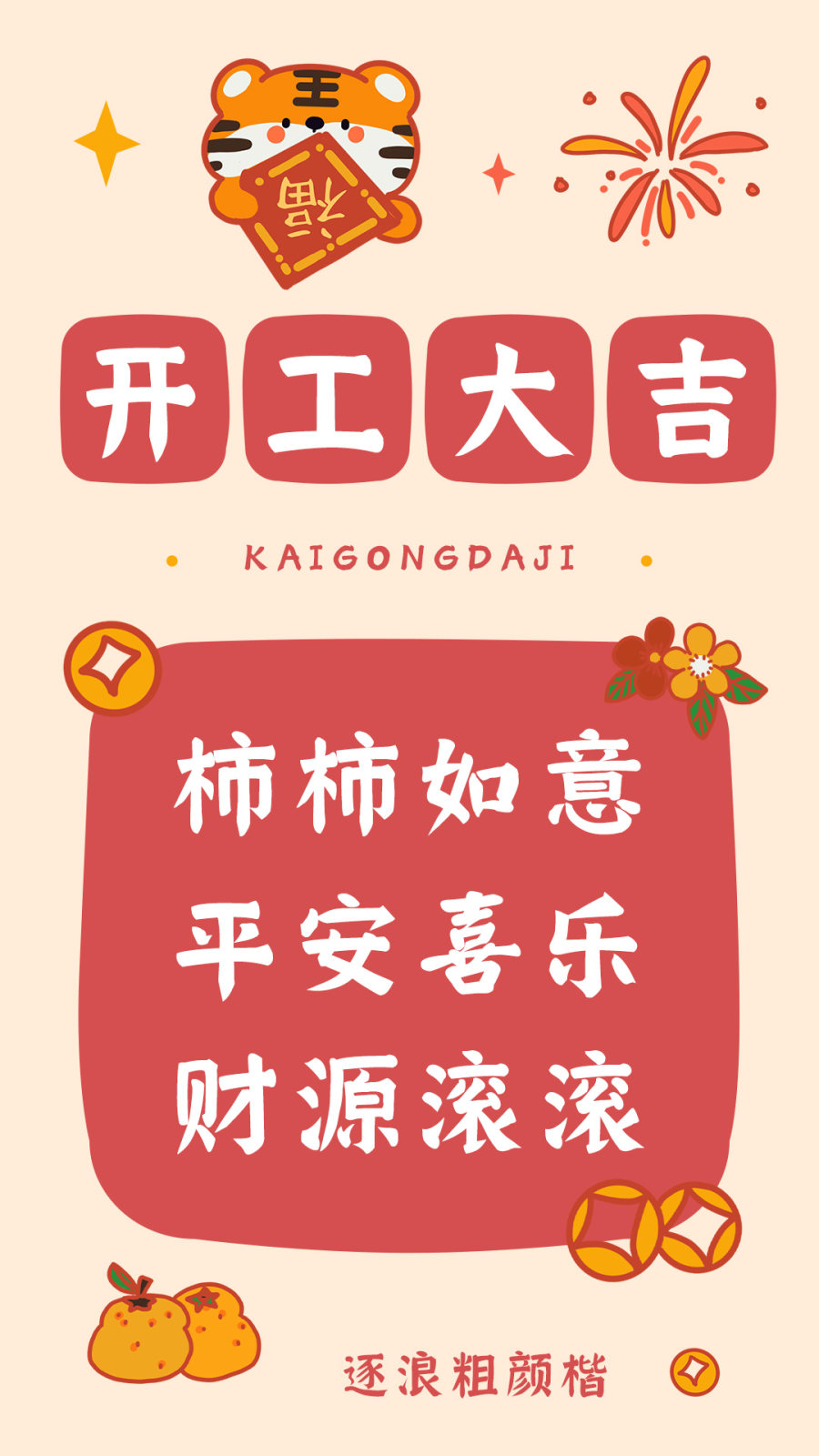
逐浪粗颜楷是逐浪字体首款颜楷字体,兼具颜体和楷体字体特色,给你古朴别致的古风字体韵味。
创作规范:
撇画如柳叶小刀出尖锋、略拉长
横加粗口形露耸肩
上点加粗竖画下方当为粗垂针或大刀形
竖还可以带勾
字形入笔追求传统,多采用传统的藏锋左切结构(避免右倾刀锋结构)
筋骨丰满遒劲有力
内敛如弓拉满弦
是不可多得的现代经典颜体字库。